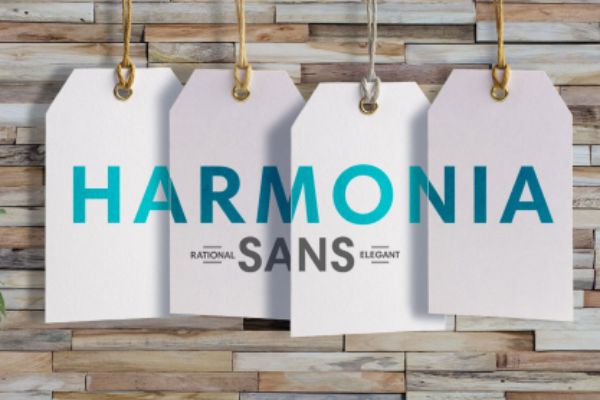
Harmonia Sans™ Pro Bold
Harmonia Sans 字体完美融合了当代几何无衬线字母形状和经典书法比例,为了在所有字母和版本中实现最大程度的易读性。Harmonia Sans 几乎适合所有印刷应用,从低分辨率显示器上的文本到高分辨率印刷,到建筑标牌。OpenType Pro 字体还提供扩展字符集,支持大多数中欧和许多东欧语言。